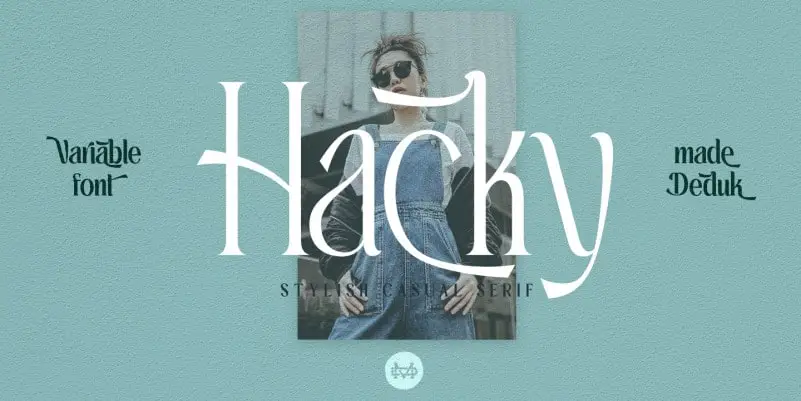
Hacky – Luxury Serif Font Family – Download Grátis
Hacky Serif é uma família de tipo serif que apresenta um estilo sofisticado e de luxo, combinando elegância com modernidade. Este fonte está disponível em 9 pesos variáveis, cada um brilhante e detalhadamente projetado para criar visuais atraentes para uma ampla variedade de aplicações. Perfeito tanto para criação de logotipos profissionais quanto para embalagens de produtos elegantes, invitações de festa, camisetas personalizadas, rótulos e panfletos. Hacky Serif é a escolha perfeita para quem procura uma fonte que combinam estilo com praticidade e funcionalidade, adequada tanto para ambientes digitais quanto impressos.